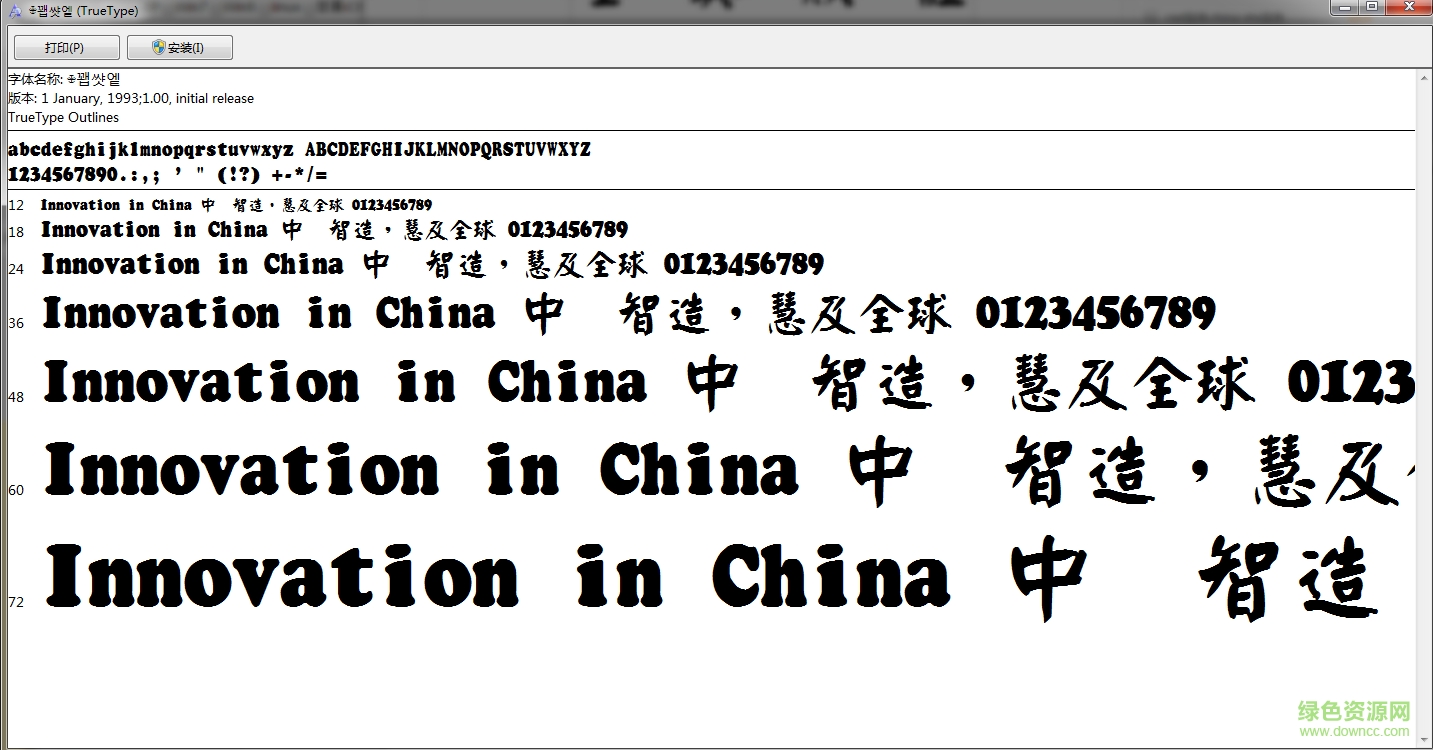
全真顏體簡(jiǎn)體字體是一款非常具有美感的書(shū)法字體,筆畫(huà)遒勁,捺撇舒展,字形雄渾飽滿,非常地有氣勢(shì),適合用在藝術(shù)設(shè)計(jì)、影視海報(bào)等領(lǐng)域,喜歡的朋友快來(lái)綠色資源網(wǎng)下載吧!
從特點(diǎn)上論,顏體形顧之簇新、法度之嚴(yán)峻、氣勢(shì)之磅礴前無(wú)古人。
從美學(xué)上論,顏體端莊美、陽(yáng)剛美、人工美,數(shù)美并舉,幽為后世立則。
從時(shí)代論,唐初承晉宋馀緒,未能自立,顏體一出,唐斗壇所鑄新體成為盛唐氣象鮮明柄志之一。